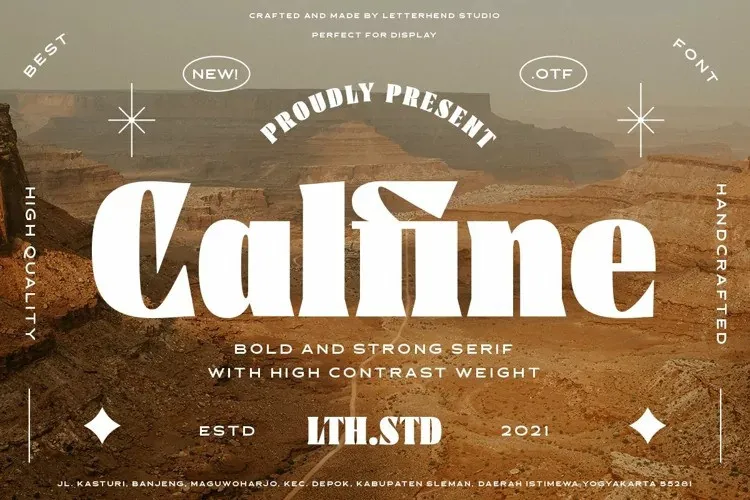
A Calfine Font é uma elegante tipografia serifada bold desenvolvida para estilos modernos e sofisticados. Essa fonte perfeitamente se adapta a aplicar como título ou destaque, tornando-a visualmente chamativa e destacável entre outros textos. Perfeita para uso em logomarcas, ela também é adequada para uma variedade de formatos formais como convites, rótulos, logos, revistas, livros, cartões de agradecimento ou de casamento, embalagens, moda e maquiagem, estaçãoaria, novelos ou qualquer tipo de finalidade publicitária. A Calfine é uma escolha perfeita para quem busca um visual forte e contemporâneo.